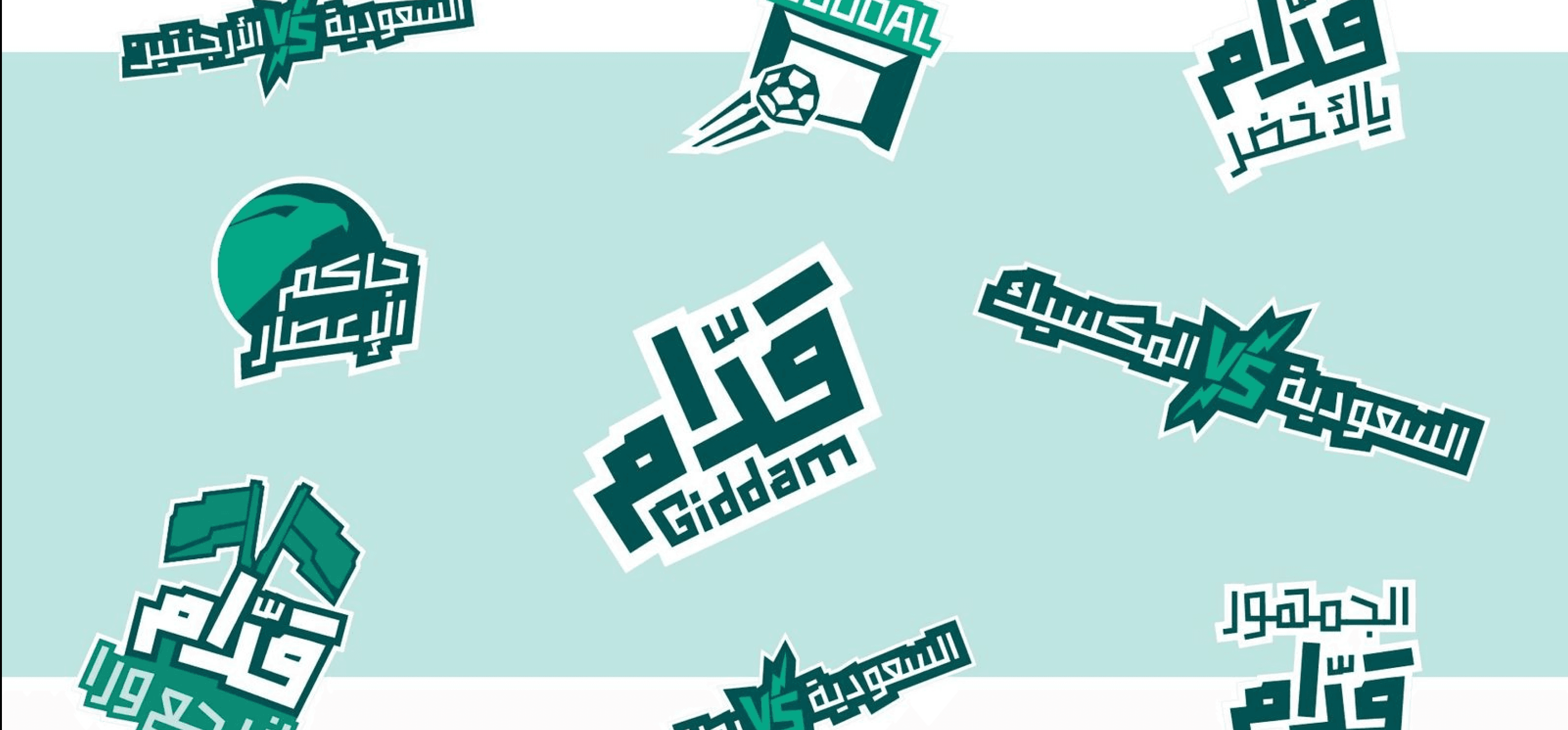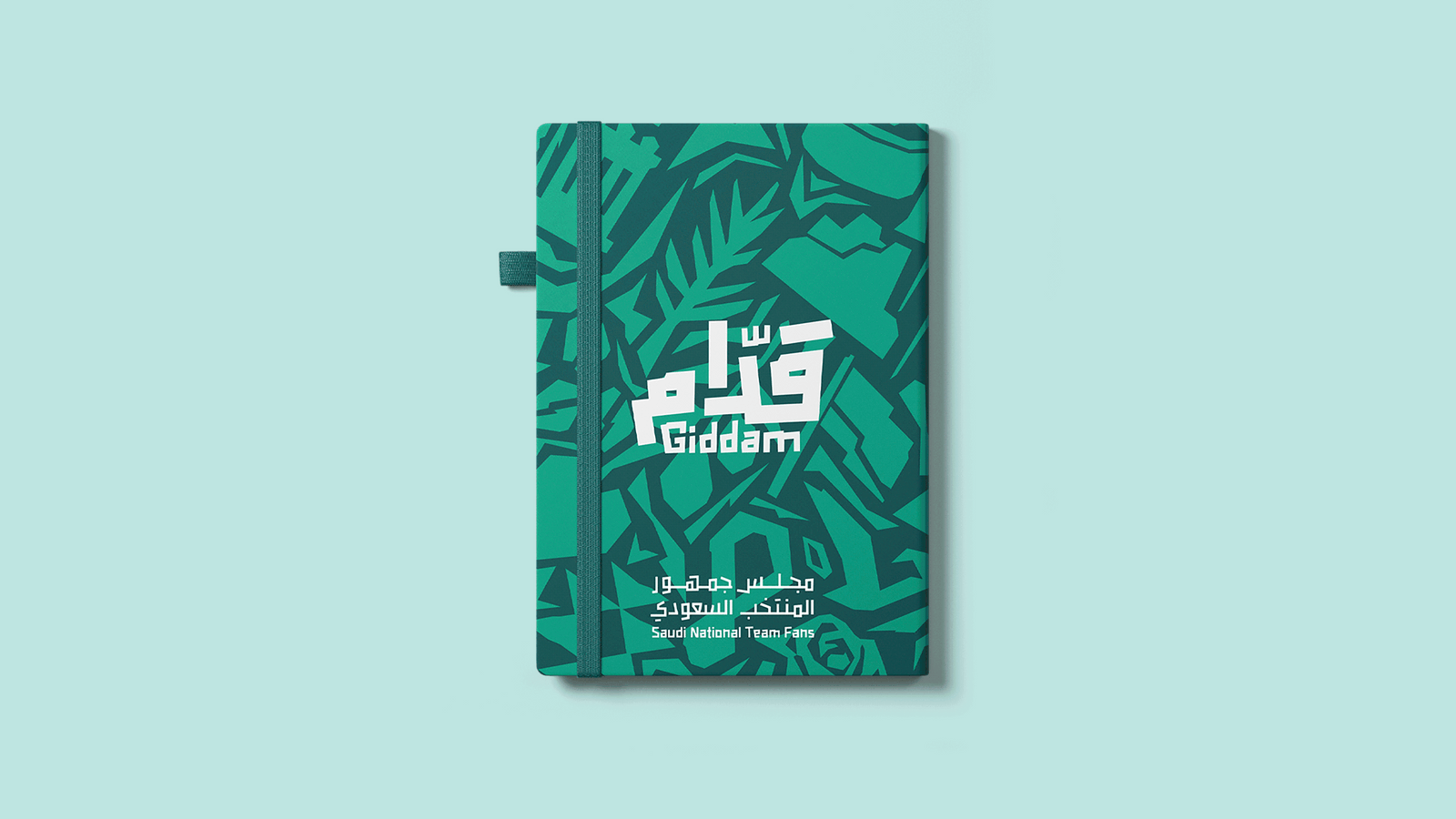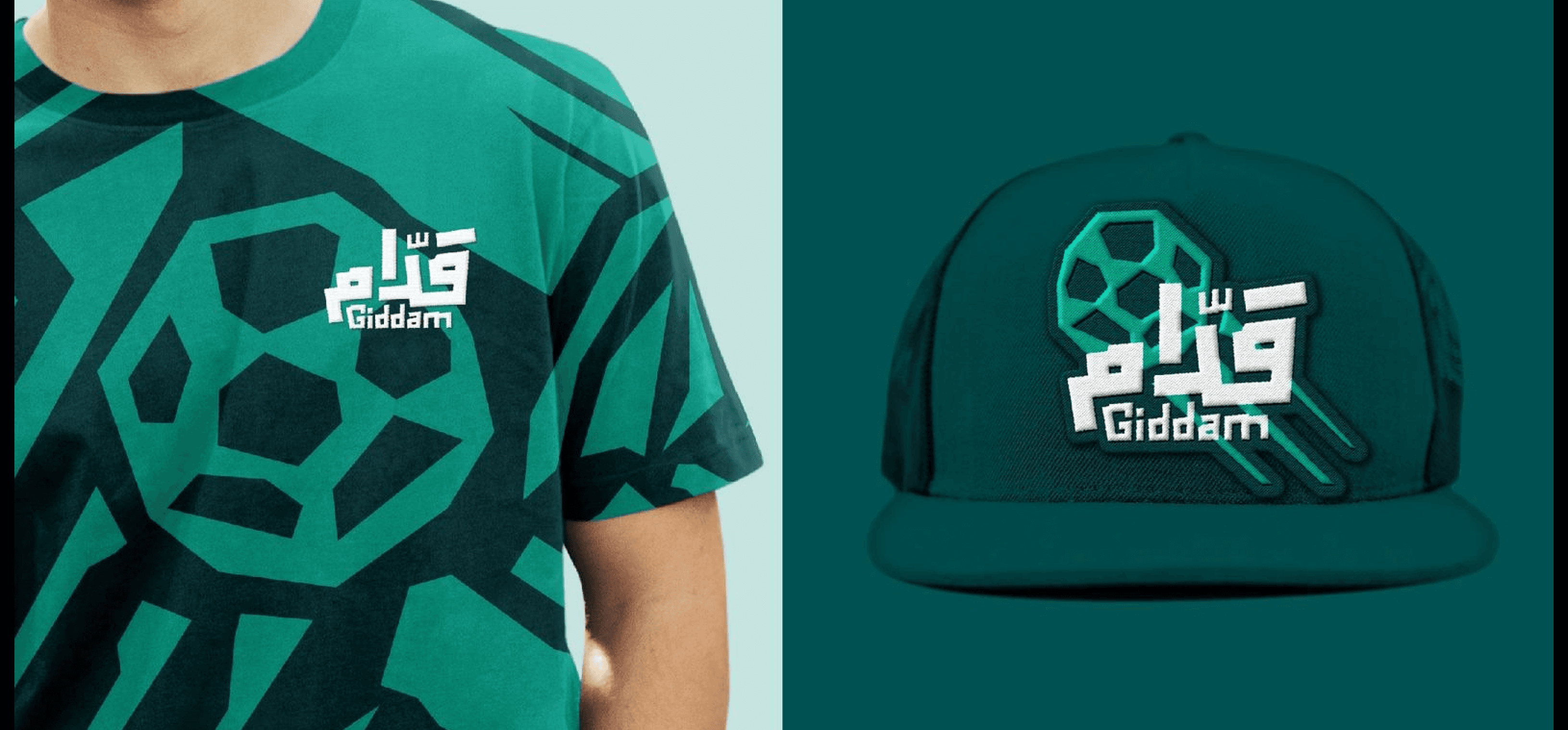
خط عربي عصري صُمم خصيصًا لعناوين حملة دعم المنتخب السعودي في كأس العالم، ويتميز بأشكاله القوية والزوايا الحادة التي تعكس روح الحماس والانتماء.
يجمع "قدّام" بين البساطة والوضوح بأسلوب بصري حديث يدعم الاستخدام في الشعارات، اللافتات، والتصميمات الرياضية والوطنية.